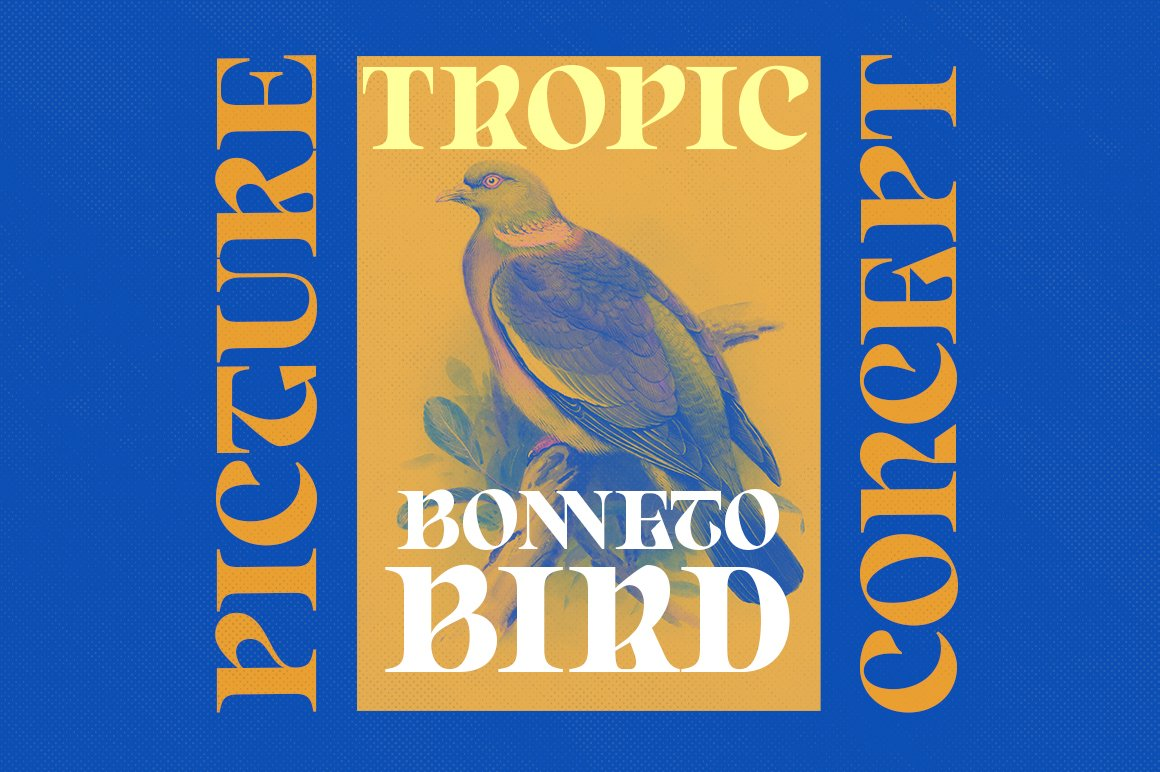
Born Spirit Font
Description de Born Spirit Font
Présentation de la police Born Spirit, une police d’affichage qui attire l’attention avec un look vintage audacieux. Des hameçons pointus et des lignes solides créent une impression de robustesse. C’est formidable de faire appel à des designers ou à des propriétaires de produits qui ont besoin de solutions pour rendre leurs créations plus élégantes et uniques.